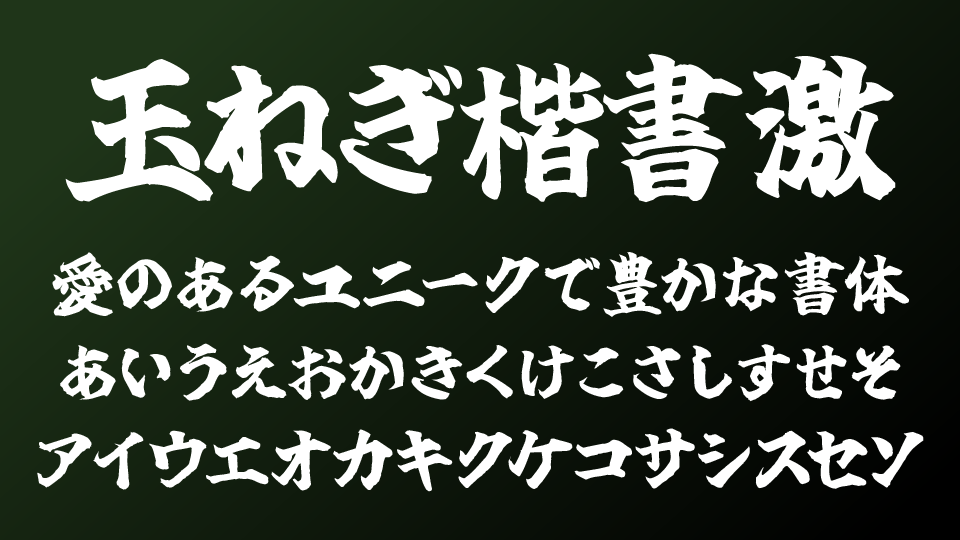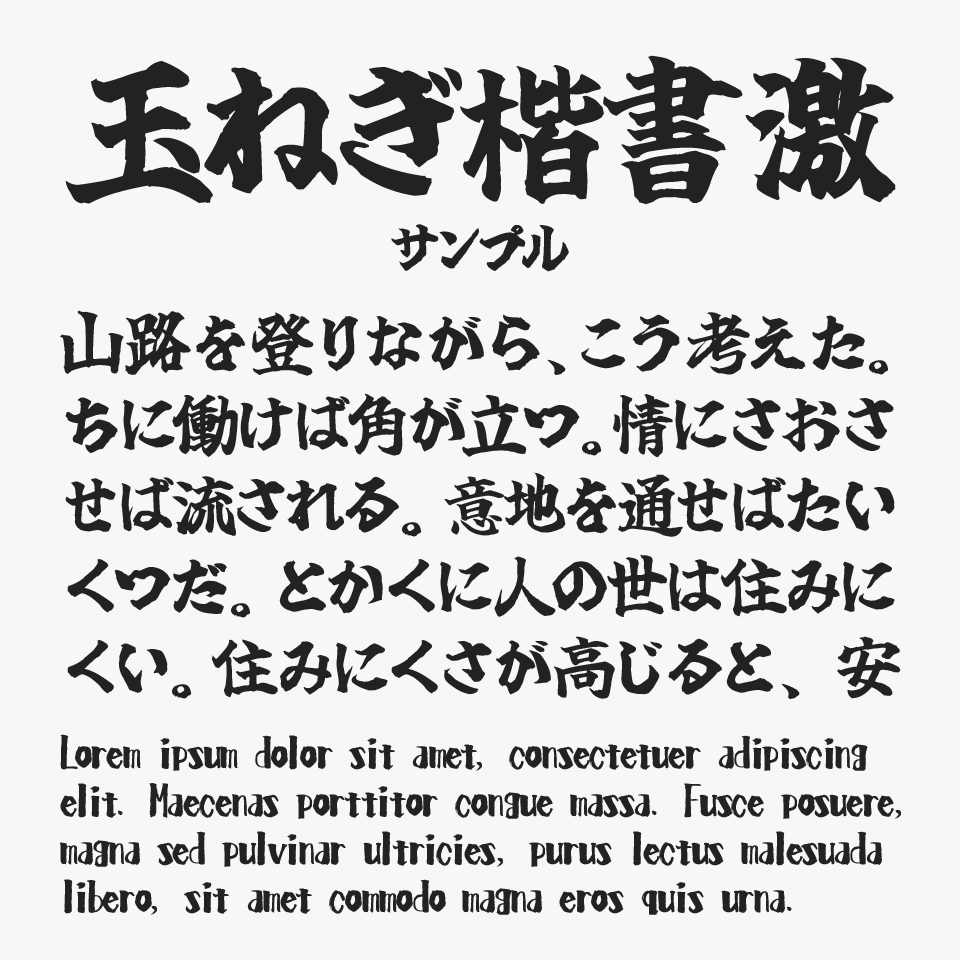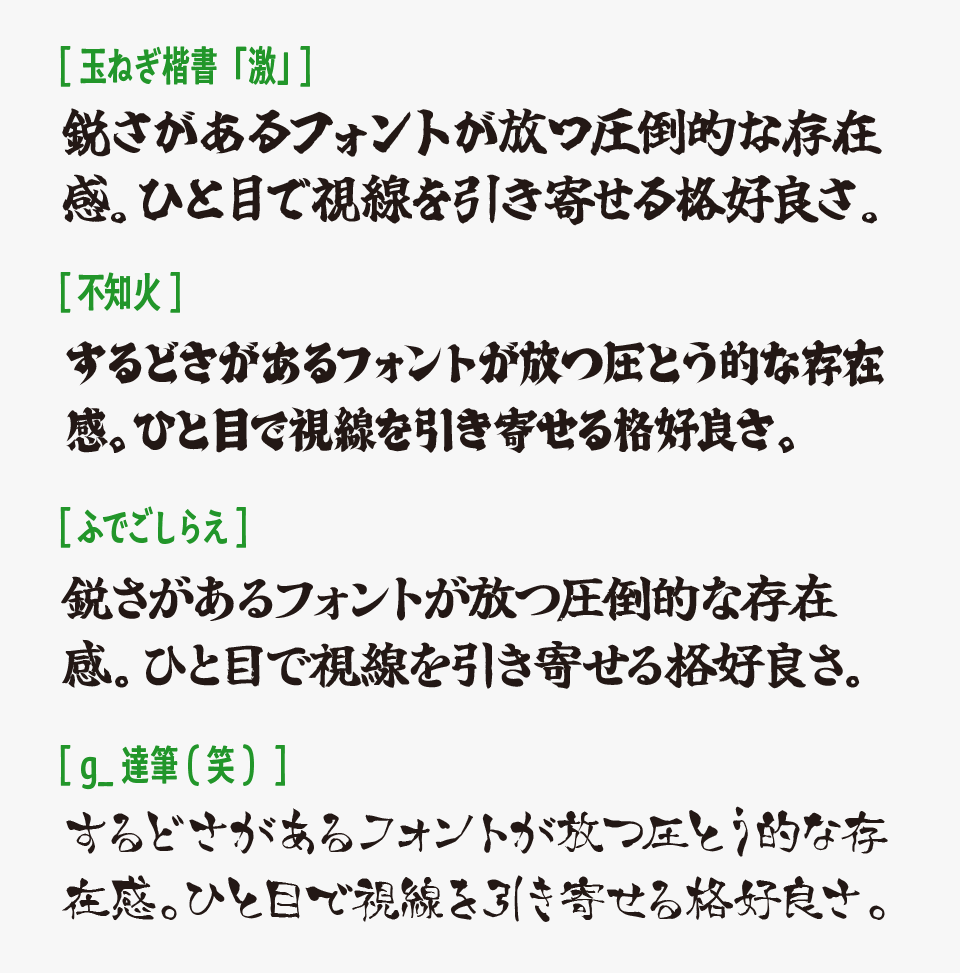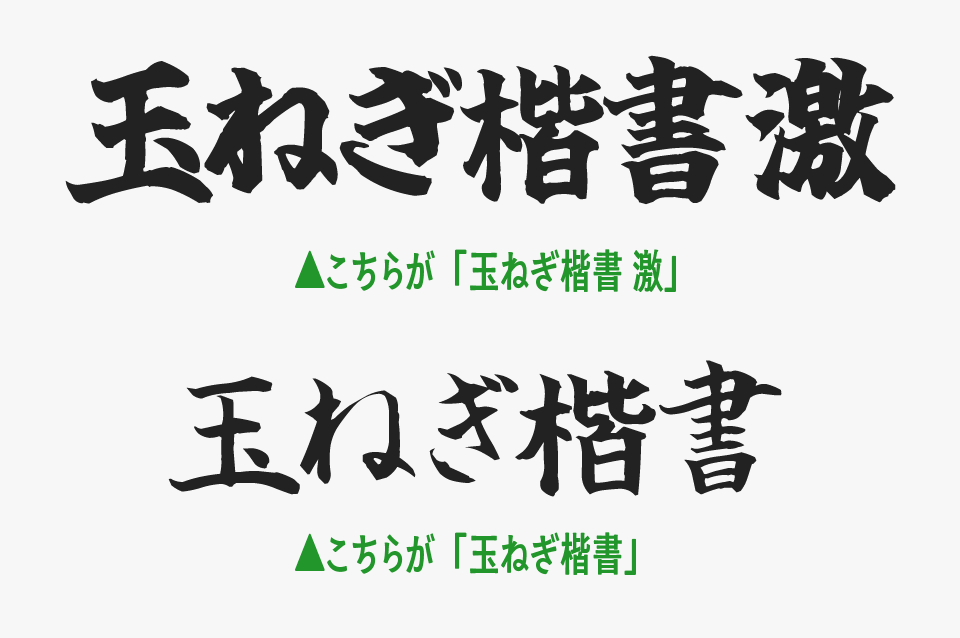
玉ねぎ楷書「激」フォントは、楷書をベースに、毛筆で勢いよく力強く書き上げたような表情が魅力の筆文字フォントです。
筆の流れや墨の勢いがダイレクトに伝わるような力強さがあり、大胆なハネやハライがしっかり強調されており、一文字ごとに”迫力”と”勢い”や”激しさ”を感じられるデザインになっているフォントです。
和風デザインやインパクトを出したいタイトル表現とももちろん相性抜群ですが、動画テロオプ、ロゴ、動画サムネイル、イベントタイトルなどに使うだけでも、一気に世界観を作り上げるビジュアルへ仕上げてくれるフォントです。
ほかの太めな筆文字系フォントと比較してみると、玉ねぎ楷書「激」フォントは、筆の“激しさ”や勢いが特に際立っているところが大きな魅力のフォントです。
比較フォントは、玉ねぎ楷書「激」と同じ太めな筆文字として「不知火」「筆ごしらえ」「g_達筆(笑)」と比較していますが、どのフォントも筆の質感がとてもステキななので、あわせてチェックしてみてください。
玉ねぎ楷書シリーズには、ウェイトが少し細い「玉ねぎ楷書」もあるので、細めの筆文字を探している方は合わせて参考ください。